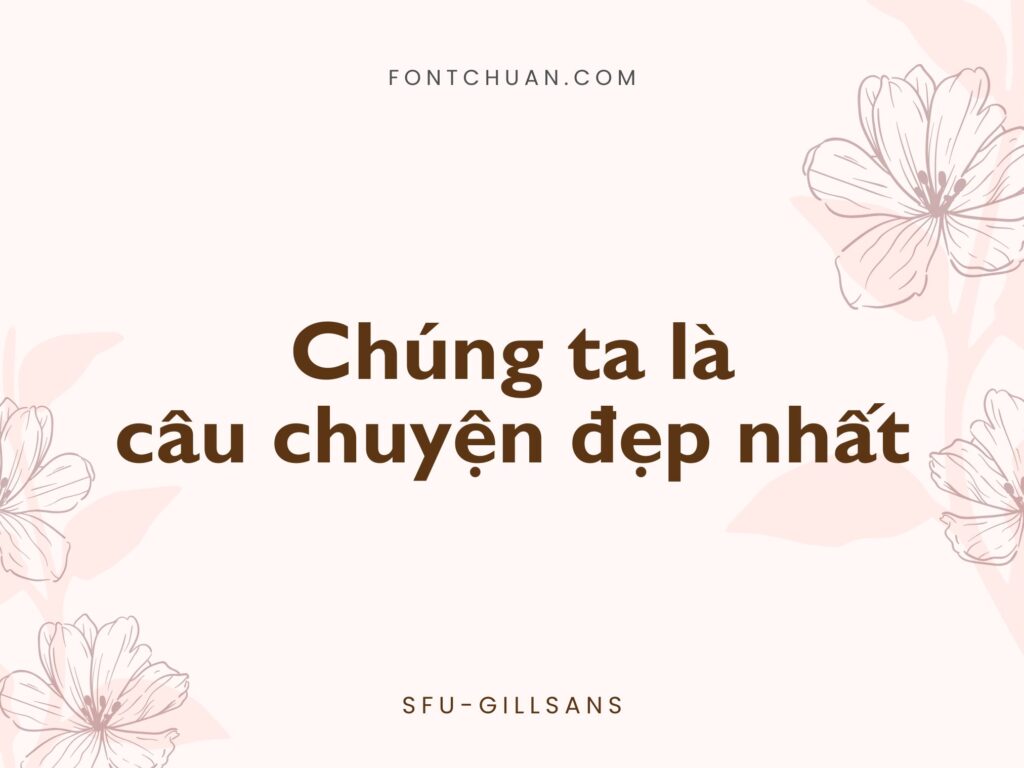
Gill Sans là một kiểu chữ sans-serif nhân văn được thiết kế bởi Eric Gill và phát hành bởi Monotype vào năm 1928. Font này được sưu tầm và đăng bởi thành viên của Font Chuẩn. Gill Sans được lấy cảm hứng từ kiểu chữ Johnston của Edward Johnston, được sử dụng cho hệ thống tàu điện ngầm London, và đã trở thành một trong những kiểu chữ biểu tượng của thiết kế Anh quốc.
Về mặt thiết kế, Gill Sans nổi bật với các đường nét sạch sẽ, hình dạng chữ cái dựa trên các hình thức cổ điển, tạo cảm giác vừa hiện đại vừa truyền thống. Font này có độ tương phản thấp, giúp tăng cường khả năng đọc ở các kích thước khác nhau. Gill Sans thường được sử dụng trong các ứng dụng như thiết kế đồ họa, in ấn, biển hiệu và nhận diện thương hiệu. Các ngành nghề như giáo dục, xuất bản, nghệ thuật và quảng cáo có thể tận dụng kiểu chữ này để tạo dấu ấn đặc biệt trong truyền thông.